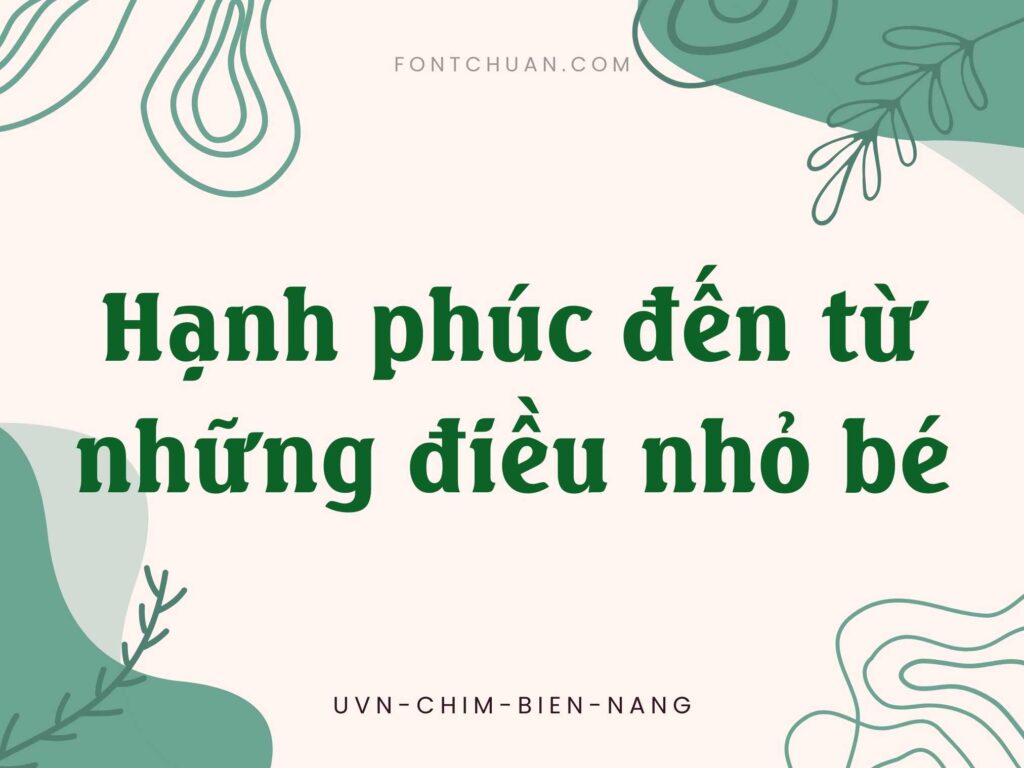
Font UVN Chim Bien Nang Việt Hóa
UVN Chim Biển Nặng là một phông chữ serif được thiết kế bởi Tom Trương vào năm 2001. Phông chữ này mang phong cách cổ điển với các đường nét đậm và rõ ràng, tạo nên sự trang nhã và dễ đọc trong thiết kế. UVN Chim Biển Nặng hỗ trợ đầy đủ các ký tự tiếng Việt, giúp người dùng tại Việt Nam dễ dàng sử dụng trong các dự án sáng tạo của mình.
Với thiết kế thanh lịch và rõ ràng, UVN Chim Biển Nặng phù hợp cho các ứng dụng như văn bản dài, sách, tạp chí, thiết kế logo và các ấn phẩm cần sự nhấn mạnh. Trong lĩnh vực sự kiện, phông chữ này có thể được sử dụng trong các dịp như hội thảo, triển lãm và các sự kiện văn hóa. Ngoài ra, UVN Chim Biển Nặng cũng thích hợp cho các ngành nghề như thiết kế đồ họa, in ấn và xuất bản.